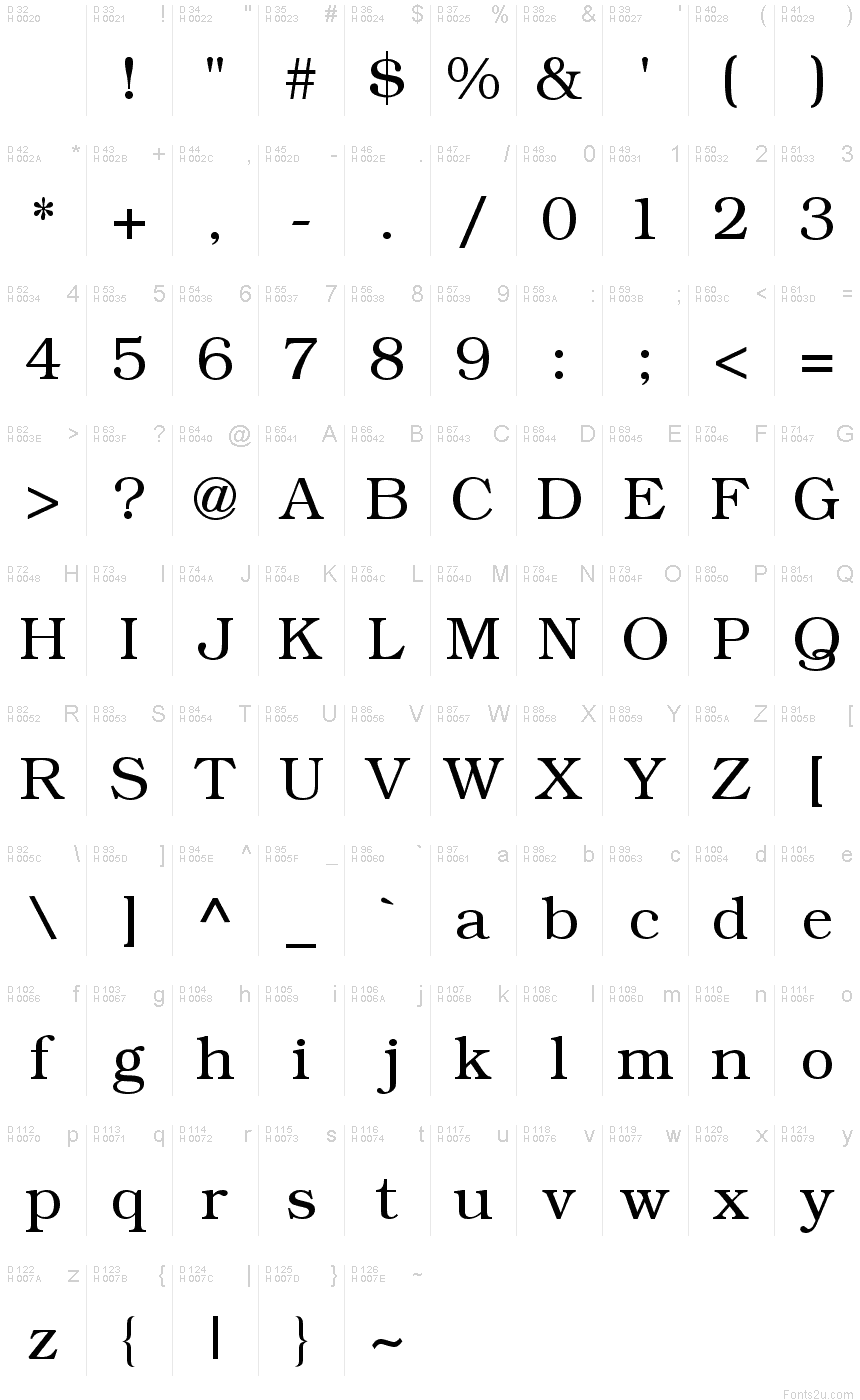
ER Bukinist 1251
ER Bukinist 1251 autorstwa Gavina Helfa to darmowy krój pisma typu oldstyle serif o spokojnym, literackim charakterze. Solidne pionowe linie, miękkie krzywizny i lekko rozszerzane szeryfy nadają mu książkowe ciepło, zachowując przy tym doskonałą czytelność nawet w małych rozmiarach. Sprawdza się doskonale, gdy potrzebujesz czegoś, co wygląda tradycyjnie i poważnie, ale nie jest przy tym sztywne.
ER Bukinist 1251 wnosi spokojny autorytet do składu książek, okładek powieści historycznych, esejów, projektów redakcyjnych, czasopism literackich i tomików poezji. Rytm liter sprawia, że długie teksty czyta się komfortowo, a subtelne detale dodają charakteru nagłówkom i cytatom. Ten darmowy font świetnie łączy się z czystym krojem bezszeryfowym w podpisach czy nawigacji – wystarczy ustawić szeryfy nieco większe, aby uzyskać efektowny i wygodny tekst.